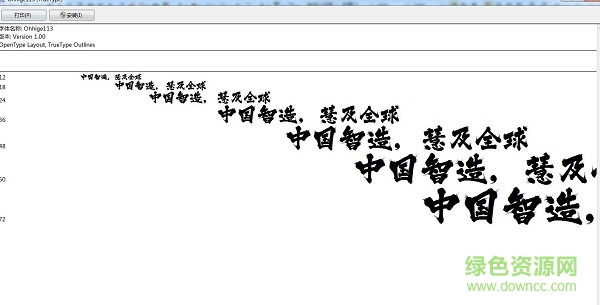
軟件介紹 軟件標(biāo)簽: 大髭字體 白舟字體 大髭日系書法字體是一套實用性與藝術(shù)性兼?zhèn)涞母咂焚|(zhì)書法字體,包含了大髭115字體和大髭113字體,線條流暢瀟灑,極其美觀,可以滿足用戶的不同需要,喜歡朋友快來下載吧!白舟字體推薦白舟侍書體美術(shù)字體 簡/繁體授權(quán):免費軟件 WinAll, WinXP, Win7大?。?.0M語言:中文白舟侍書體美術(shù)字體是一款常用于ps中的電腦字體,字體線條較粗,筆畫蒼勁有力,效果醒目,歡迎有需要者在綠色資源網(wǎng)下載!字體安裝說明1、首先選中你下載的打包字體,并解壓你下載的字體壓縮包;2、WinVista\Win7\Wi下載地址白舟魂心字體 完整版授權(quán):免費軟件 WinAll, WinXP, Win7大?。?.7M語言:中文白舟魂心書體字體是一款大氣沉穩(wěn)的白舟字體,字形粗壯厚重,構(gòu)造嚴(yán)謹(jǐn),很有韻味,打印出來的效果也非常出色,需要的朋友歡迎在綠色資源網(wǎng)下載!字體安裝說明:Win7\Win8\Win10系統(tǒng):鼠標(biāo)右鍵單擊字體文件,然后點擊>"下載地址字體結(jié)構(gòu)介紹單體字:一個偏旁單獨構(gòu)成的字。合體字:兩個或兩個以上偏旁組合成的字。大髭字體安裝方法方法一:控制面板/字體/文件/安裝新字體;方法二:直接將字體復(fù)制到C:\WINDOWS\Fonts。方法三:針對win7系統(tǒng),用戶只需選中字體右鍵安裝即可。 軟件截圖 上一張下一張(1 / 1) 安裝詳細截圖 猜你喜歡 白舟字體 白舟字體 白舟字體大全是綠色資源網(wǎng)小編為大家精心整理的白舟字體合集,包含了幾十款常用的白舟字體,可廣泛的應(yīng)用于排版印刷、廣告設(shè)計、影視設(shè)計、平面設(shè)計等領(lǐng)域! 查看更多>> geikaisuikou 3.16M/中文/5.0/下載 隼風(fēng)字體簡體 5.66M/中文/6.6/完全版下載 bukotsustd u regular 5.41M/中文/8.0/下載 大髭日系書法字體 7.61M/中文/1.8/下載 hot-ninja std r字體 5.39M/中文/2.7/下載 白舟極太行書 1.29M/中文/10.0/下載 其他版本下載 標(biāo)題 大小 更新日期 下載 下載地址 電腦版 大髭日系書法字體 點擊報錯 軟件無法下載或下載后無法使用,請點擊報錯,謝謝! 關(guān)閉報錯反饋 請描述您所遇到的錯誤,我們將盡快予以修正,謝謝! *必填項,請輸入內(nèi)容 本類最新 dreamweaver字體庫 首爾南山體字體 v1.06 官方版 潮字社風(fēng)云簡ttf 潮字社凌渡鯤鵬簡體字體 潮字社曾玉波手書簡字體 微博慧心字體 相關(guān)文章 Photoshop字體安裝使用方法和技巧 如何解決“無法新增字體”問題 Win 7系統(tǒng)安裝字體方法 網(wǎng)頁字體大小設(shè)置方法 怎么改網(wǎng)頁字體大小 在Linux系統(tǒng)中安裝字體的幾種方法 windows7字體顯示問題:打開某些程序的時候顯示的是亂碼 用戶評論 熱門評論 最新評論 發(fā)表評論 查看所有評論(0) 昵稱: 請不要評論無意義或臟話,我們所有評論會有人工審核. 字?jǐn)?shù): 0/500 (您的評論需要經(jīng)過審核才能顯示)